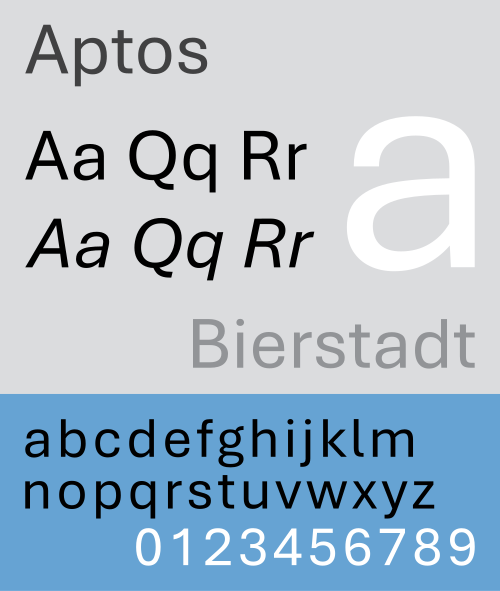
| カテゴリ | サンセリフ |
| 分類 | ネオグロテスク[1] |
| デザイナー | スティーブ・マテソン |
| 委託先 | マイクロソフト |
| 鋳造所 | マイクロソフト株式会社 |
| 作成日 | 2019年[2] |
| リリース日 | 2023 |
| デザインは | ヘルベチカ アリアル |
| 別名 | ビアスタット |
Aptosは元々Bierstadtという名前で、スティーブ・マテソンが開発したネオグロテスクスタイルのサンセリフ 書体です。[3] 2023年にMicrosoft Officeスイートの新しいデフォルトフォントとしてリリースされ、以前使用されていたCalibriフォントに代わるものです。[4]
Aptosとその兄弟フォントであるAptos Display、Aptos Narrow、Aptos Mono(等幅フォント)、Aptos Serif(セリフフォント)は、 Microsoftのクラウドサービスを通じてMicrosoft 365加入者に提供されています。 [5]
特徴
Aptos には、Light、Light Italic、Regular、Italic、Semibold、Semibold Italic、Bold、Bold Italic、Extrabold、Extrabold Italic、Black、Black Italic のスタイルがあります。
この書体には、読みやすくするいくつかの独特な特徴がある。[6] [7]
- Arialの斜めのストロークの終わりとは対照的に、Helveticaに基づいた水平および垂直のストロークの終わりを持ちます。
- 小文字「a」の特徴的な末尾を削除し、小文字「t」のように小文字「l」(L) に追加することで、大文字「I」(i) との混同を防止しました。
- 大文字の「O」と「R」、小文字の「a」の形が少し不規則です。
- ヘルベチカのような1階建ての文字ではなく、角度のついた茎を持つ2階建ての小文字「g」を持ち、大文字の「G」は丸みを帯びていて、突起がありません。
- 大文字「R」の小さなスイングテール。
- 小文字の「b」、「c」、「p」と大文字の「C」は輪郭が広いです。
- Arial や Helvetica の四角い点とは対照的に、句読点、発音区別記号、小文字の「i」と「j」には丸い点が付きます。
- 数字「1」の湾曲した上部フラグは Arial に基づいています。
- 数字「7」の斜めの幹。
- 大文字の「Q」の湾曲した尾部がボウルと接します。
Aptosにはラテン文字、ラテン拡張文字、ギリシャ文字、キリル文字の文字が含まれています。Aptosのイタリック体は機械的に傾斜しているのではなく、個別に再描画されています。イタリック体にはキリル文字を除いて筆記体がありません。キリル文字の文字の形は、Calibriの真のイタリック体とは対照的に、直立した文字の斜体です。 [8]
歴史
Aptosはもともとコロラド州ロッキー山脈のビアスタット山にちなんでビアスタットと名付けられました。[6] 20世紀半ばの典型的なスイスのフォントに基づいています。このフォントは、HelveticaやArialフォントの感覚を呼び起こすことが意図されていました。[6] 2021年に、Microsoft OfficeおよびMicrosoft 365アプリケーション用の他の4つのフォント(Grandview、Seaford、Skeena、Tenorite)とともに導入されました。その結果、Bierstadtは、2007年に導入されたMicrosoft Office標準フォントCalibriの後継となる可能性があると考えられていました。[9]
2023年7月、マイクロソフトは、カーニングと行送りを若干変更し、カリフォルニア州アプトスにちなんで改名されたものの、BierstadtがCalibriの後継となると発表した。[4] [10]